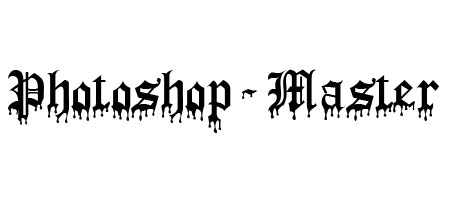
Шрифт - Blood Of Drakula
Интересный шрифт без поддержки русского языка.
А по мне красивый.
а есть такой же только русский?^^
Да!!!с падтёками и вправду перебор +1, ненрався
С подтеками перебор, можно не кровь дракулы, а сопли дракулы назвать